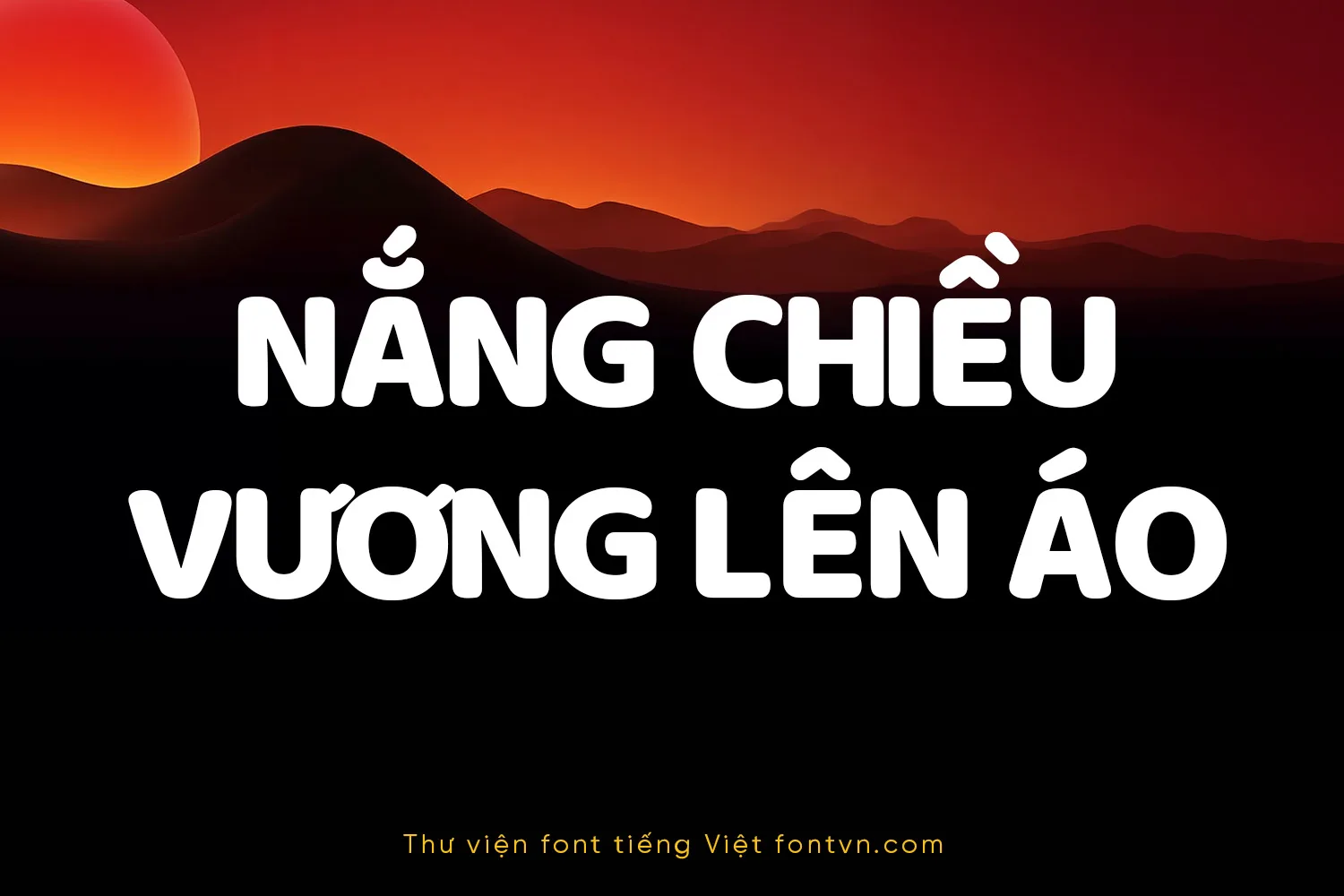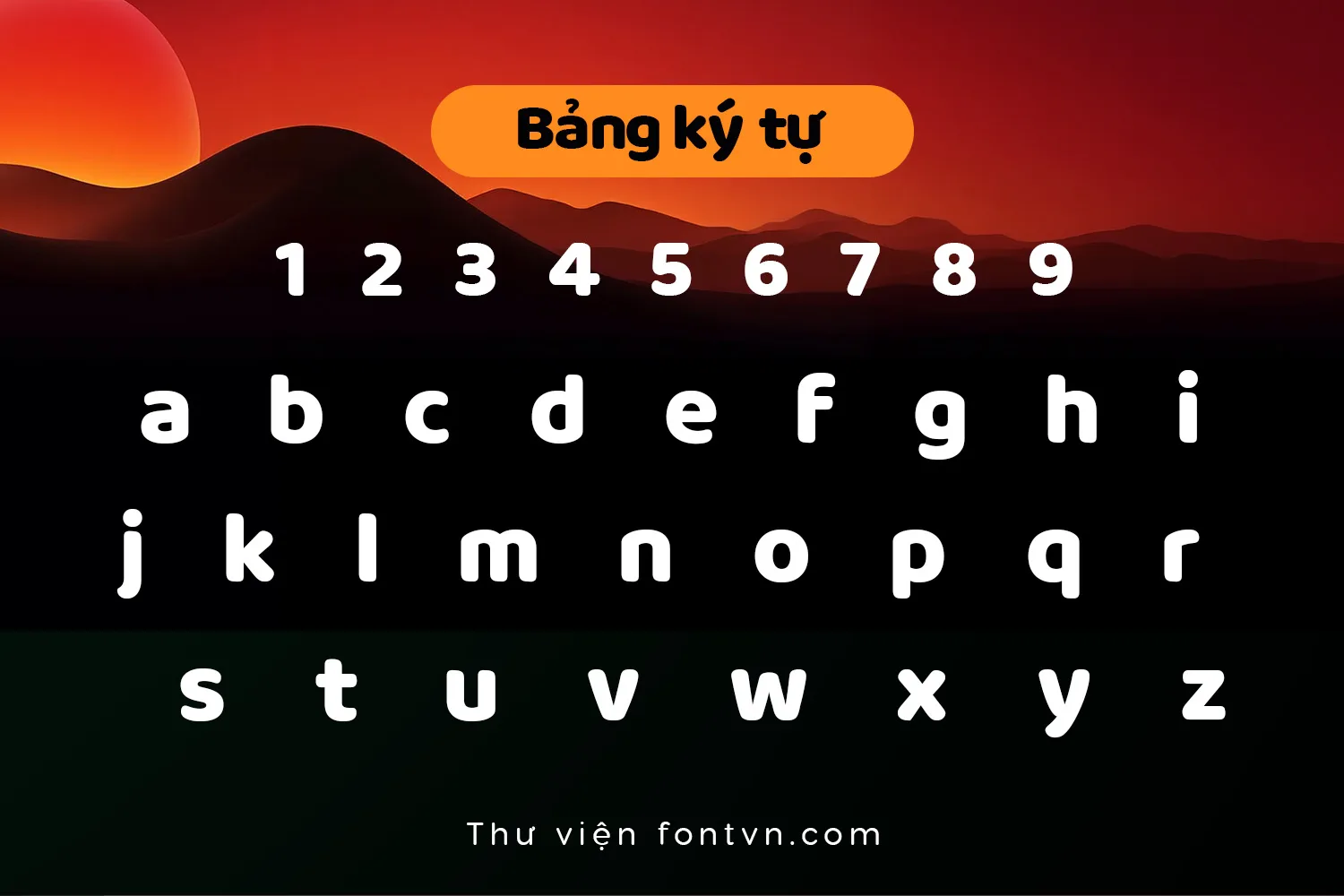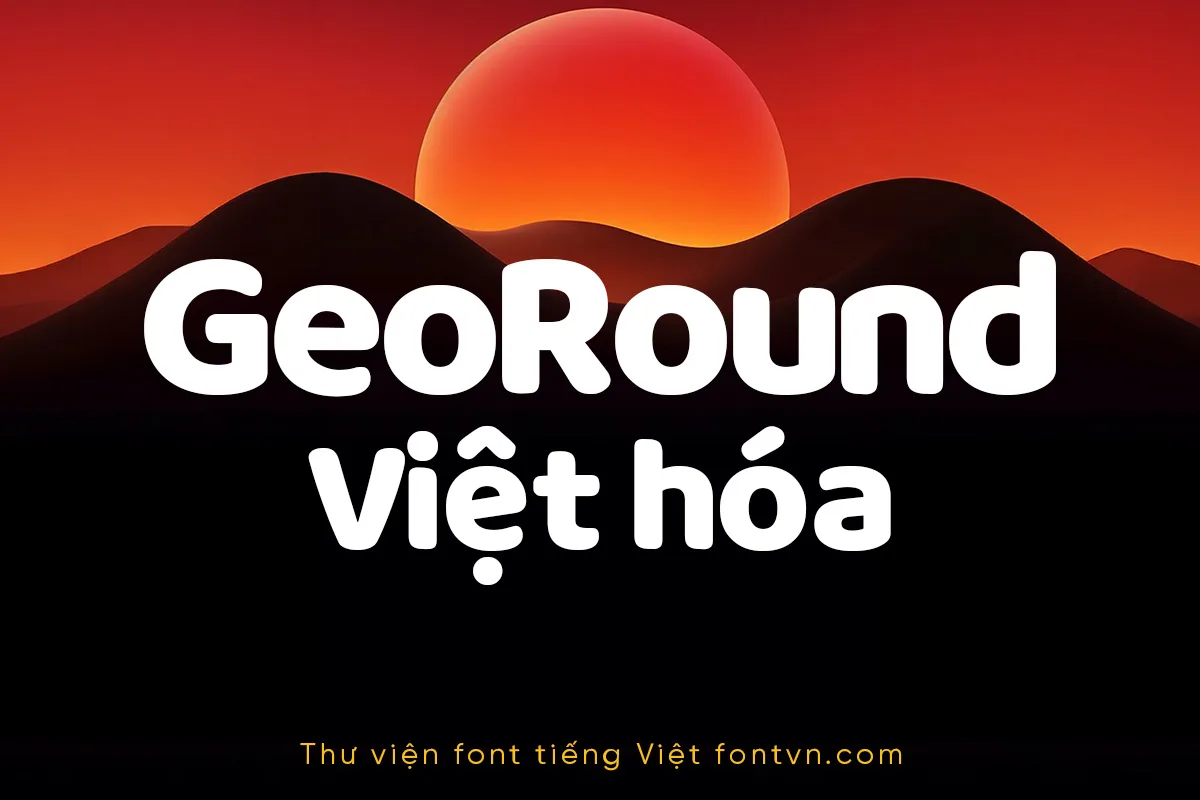
DVN GeoRound Việt hóa – Font chữ bo tròn nét đậm phù hợp cho dự án Kid, trẻ em
DVN GeoRound Việt hóa thuộc nhóm phân loại geometric rounded sans-serif với cấu trúc typeface ở mức heavy weight. Đặc điểm kỹ thuật cốt lõi của bộ font nằm ở độ tương phản nét (stroke contrast) cực kỳ thấp, kết hợp cùng các terminal và góc giao (vertex/apex) được xử lý bo tròn hoàn toàn để tạo ra các hình khối dạng capsule đồng nhất. Typeface này sở hữu x-height lớn cùng ascender và descender tương đối ngắn, giúp nén không gian theo chiều dọc một cách hiệu quả. Trong quá trình Việt hóa, hệ thống dấu thanh (diacritics) đã được thực hiện các bước tinh chỉnh quang học (optical adjustments) chuyên sâu, thiết lập khoảng cách (clearance) chuẩn xác với base glyph nhằm triệt tiêu hiện tượng dính nét và bảo toàn tuyệt đối legibility khi render ở các kích thước lớn (display size).
Về mặt công năng ứng dụng, cấu trúc khối hình học bo tròn của DVN GeoRound đáp ứng trực tiếp các tiêu chuẩn thị giác vật lý (visual stability) cần thiết cho các dự án thiết kế hướng tới tệp người dùng trẻ em. Typeface này phát huy tối đa hiệu suất hiển thị khi được thiết lập ở vai trò headline, logotype, tiêu đề sách giáo dục, hoặc hệ thống typography chủ đạo trên bao bì sản phẩm (packaging). Trong môi trường UI/UX kỹ thuật số, visual weight đồ sộ của font chữ cung cấp độ tương phản hiển thị đủ mạnh để phân cấp thông tin, cực kỳ phù hợp để tích hợp vào các layout dạng bento-box, thiết kế hero banner đi kèm fluid gradients, hoặc cấu trúc các nút CTA khổ lớn trên nền tảng web và ứng dụng tương tác thiếu nhi.